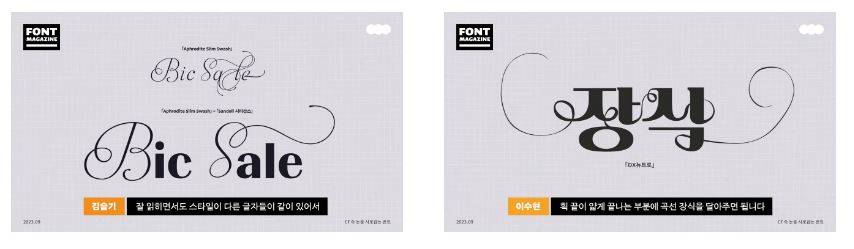
CF 광고 속 눈길을 사로잡은 폰트는?
CF 광고 속 폰트, 평소 눈여겨보시나요?
단시간에 소비자의 눈을 사로잡아야 하는 CF 광고에서 폰트의 선택은 CF 광고의 승패를 좌우한다고 해도 과언이 아닐 거예요. 따라서 CF 광고 트렌드만 관찰해 봐도, 지금 핫한 폰트가 어떤 것인지 알 수 있는데요, 오늘은 여러 광고에서 공통적으로 보이는 폰트들의 2가지 특징을 모아왔어요. 다양한 CF 광고에 사용된 폰트 또는 레터링을 보고, 이와 유사한 폰트와 비슷하게 변형하기 좋은 폰트들의 정보를 모아 왔답니다.
여러 CF 광고에서 찾을 수 있는 공통점 첫 번째!
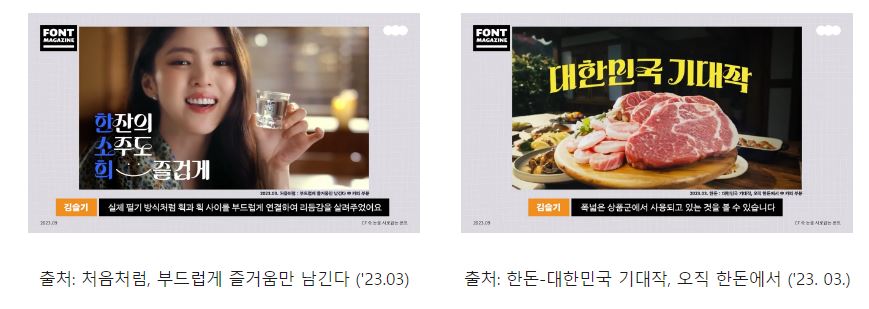
가벼운 곡선 포인트 예시부터 살펴볼까요? 처음처럼 광고의 경우, 다른 부분과 달리 중요 카피 부분에 곡선 포인트를 사용했고, 실제 필기 방식처럼 획과 획 사이를 부드럽게 연결하여 리듬감을 살려주었죠. 이외에도 한돈 광고 등 폭넓은 상품군에서 사용되고 있는 것을 볼 수 있습니다. (다양한 예시 사례는 영상에 모두 담겨있어요!)
이어서 곡선 포인트 폰트 꿀팁 나갑니다!
강한 곡선 장식은 개성과 주목도는 높여주지만 전체적으로 읽기 어려워질 수 있는데요, 이럴 때는 가독성이 좋은 폰트들 사이에 1-2개의 핵심 글자에만 장식을 주어 보세요. 잘 읽히면서도 더 새롭고 특색 있어 보이는 글이 될 거예요
또한, 한글 폰트에서 곡선을 강조한 폰트를 찾고 싶은 분들께는, 곡선형 스타일로 변형하기 좋은 폰트들을 추천드릴게요. (글자 수가 몇 안 되는 영문 폰트와 달리 한글 폰트는 최소 2천 자 이상 그려야 하기 때문에 곡선 장식이 많은 폰트는 찾기 어렵답니다.) 「TSC블랙러버」, 「DX뉴트로」는 획의 강약 대비가 있기 때문에, 획 끝이 얇게 끝나는 부분에 곡선 장식을 달아주면 나만의 곡선 포인트 뚝딱 완성이에요!
여러 CF 광고에서 찾을 수 있는 공통점 두 번째!